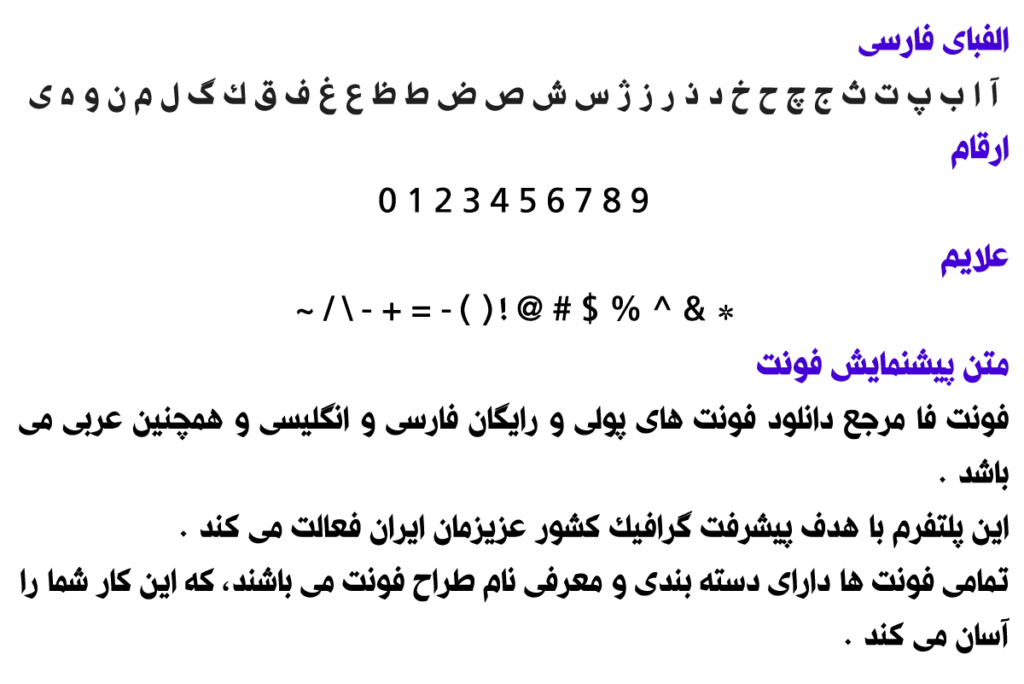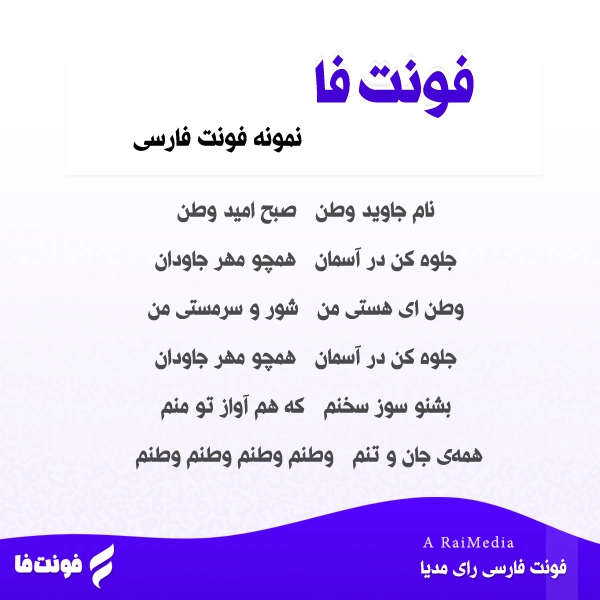
فونت فارسی رای مدیا – A RaiMedia
نوع فونت: فونت عنوان
توضیحات و معرفی فونت رای مدیا
فونت فارسی رای مدیا ( A RaiMedia ) از مجموعه فونت های آزاد می باشد، و نیز نوع فونت عنوان می باشد.
فونت خوشگل مربوط در سال 1390 طراحی و ساخته شده است.
و نیز فونت A RaiMedia در 2 وزن سنگین و پر رنگ است.
- A RaiMedia Black
- A RaiMedia Bold
شعر زیبای «وطنم» را که با این تایپ فیس نوشته شده، می توانید در تصویر زیر ببینید.